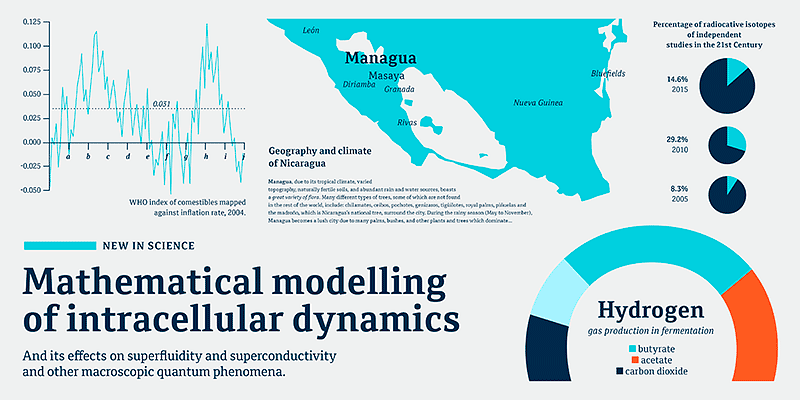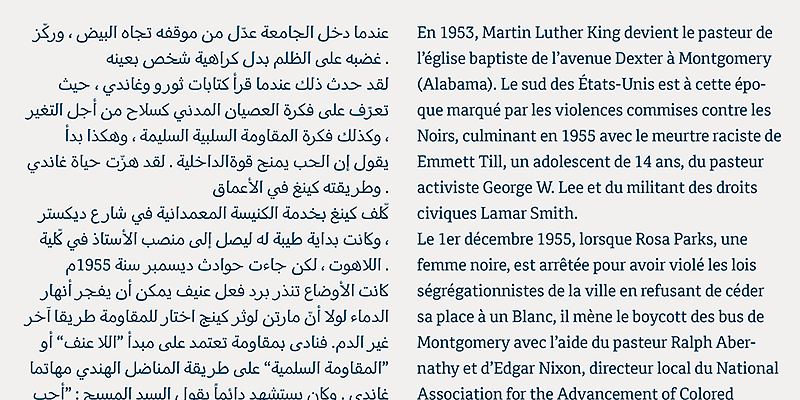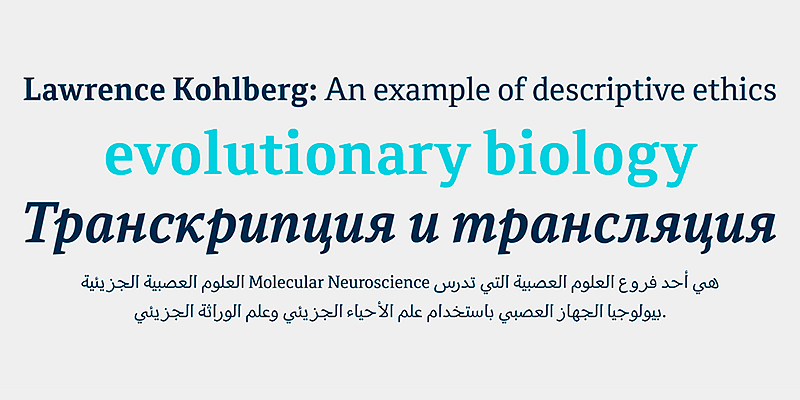
Le Cordale est une police de texte à toute épreuve, avec quatre styles traditionnels. Elle peut transmettre n’importe quel message avec clarté, efficacité, accessibilité et une élégance suprême.